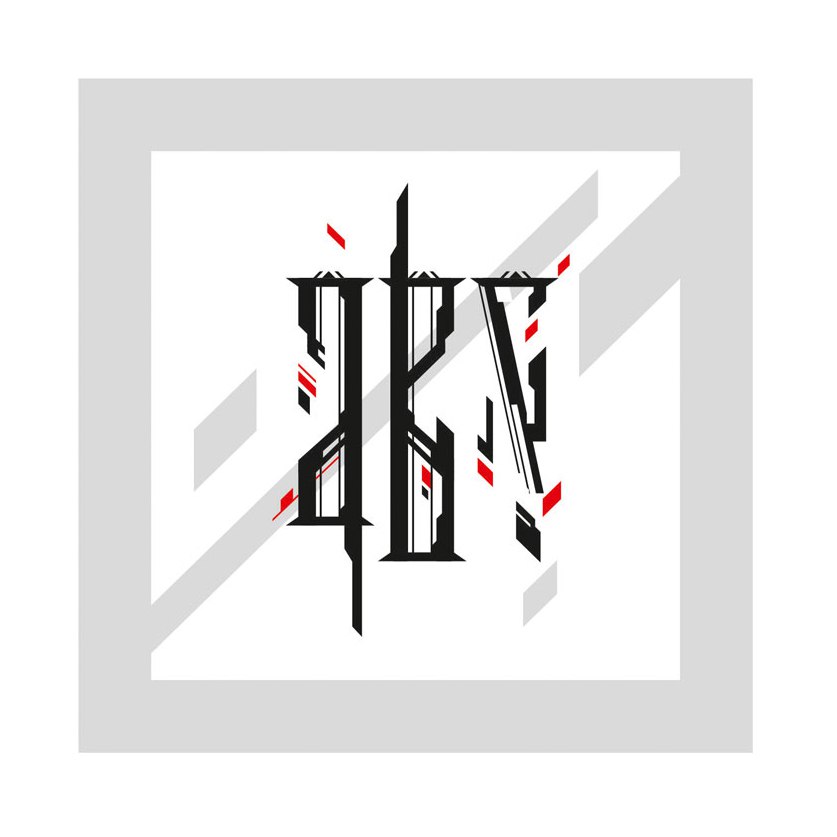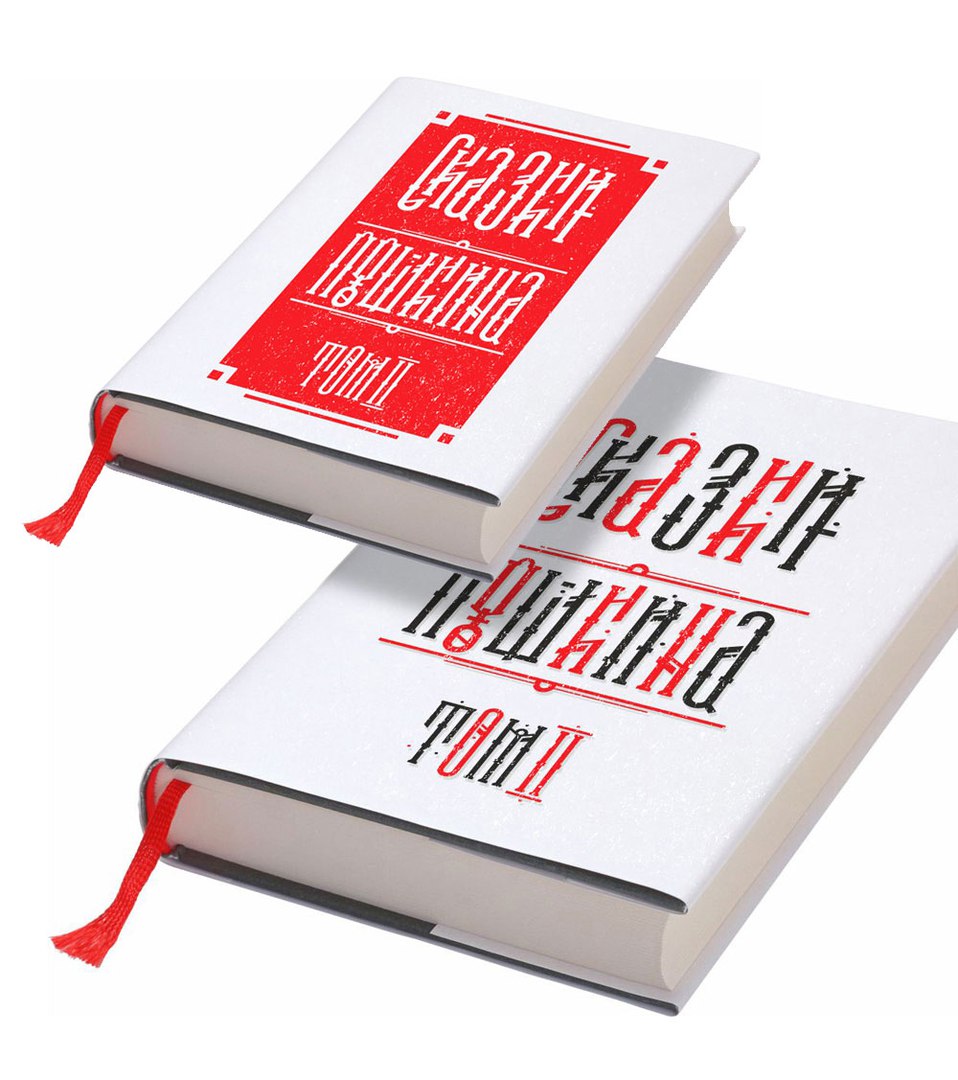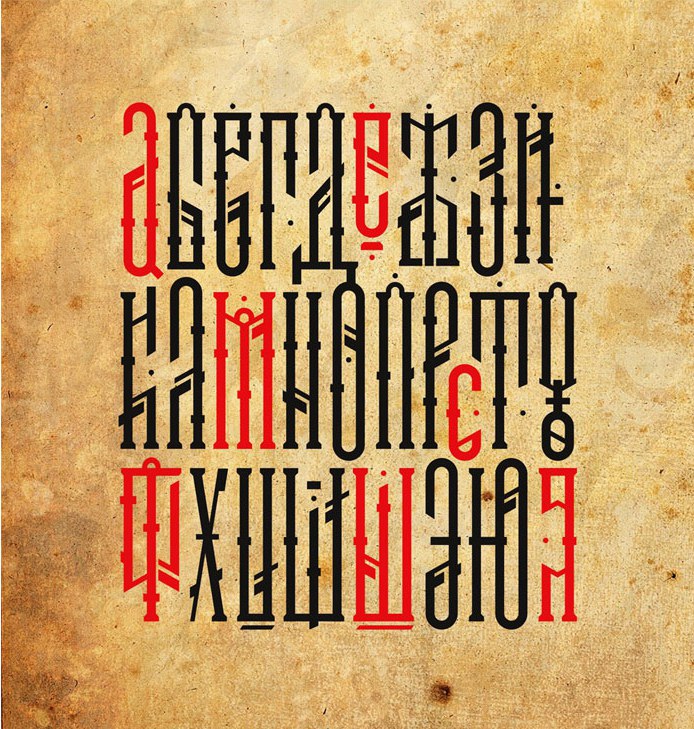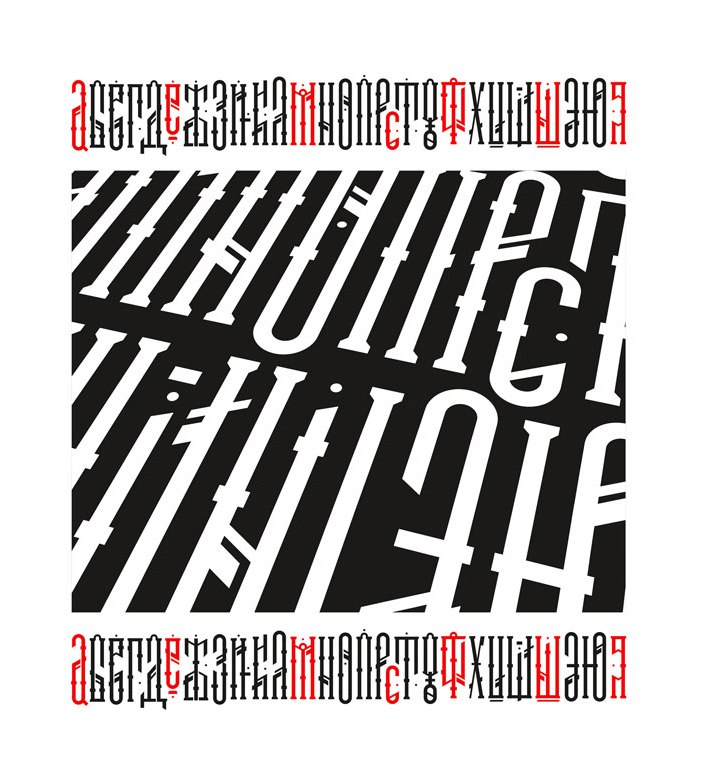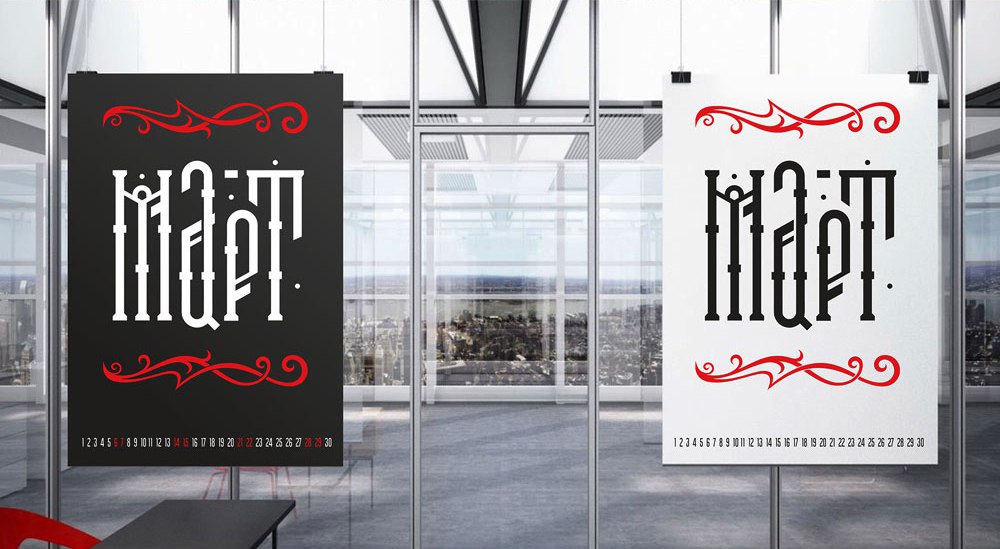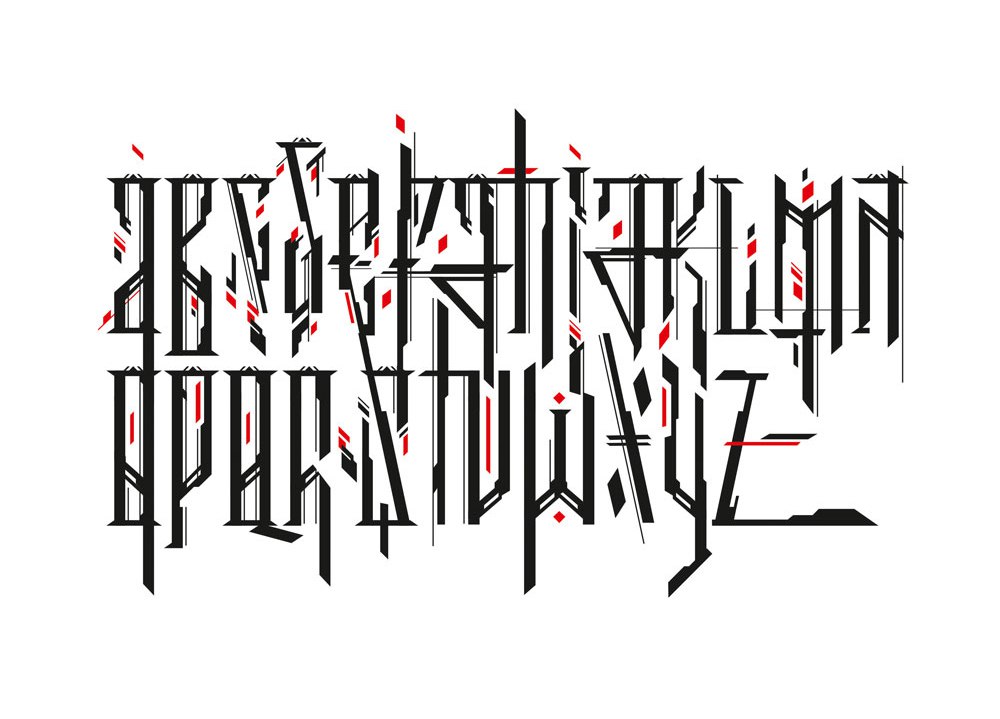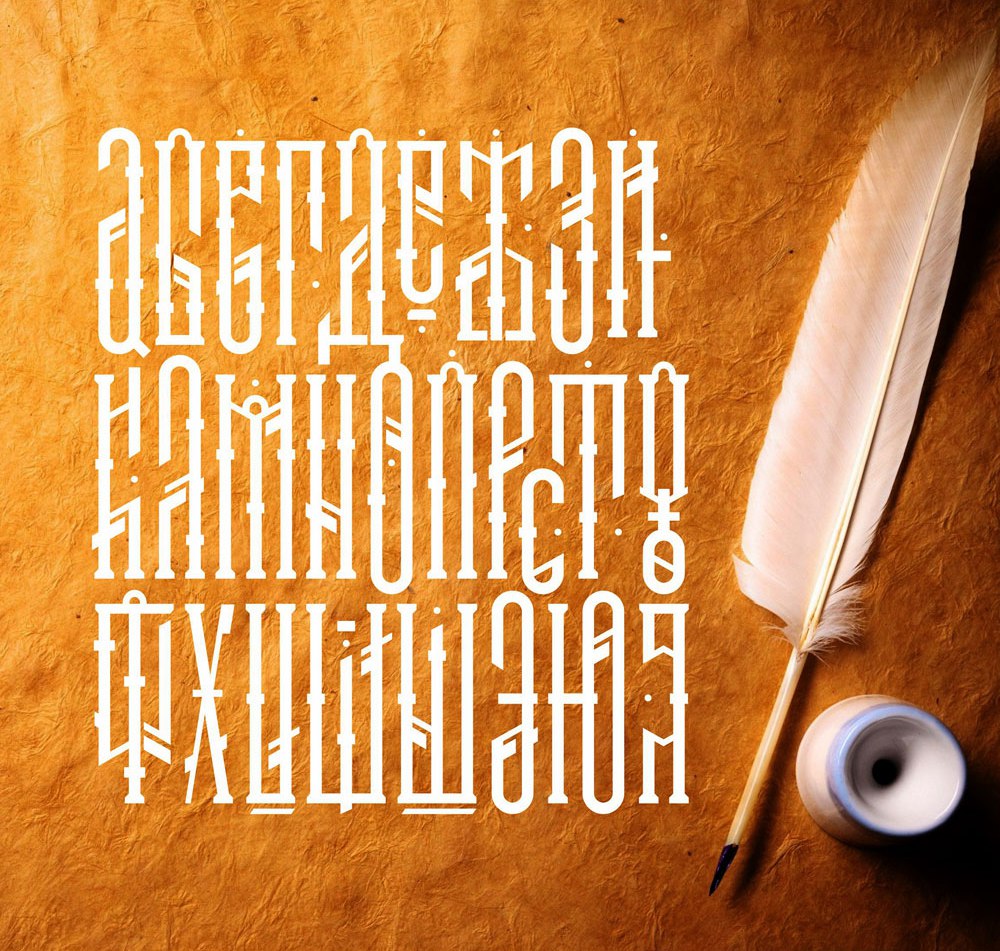
Шрифт Mart (Латиница, Кириллица)
Авторская версия русского орнаментального шрифта.
Павел Дракунов behance.net/Drakunoff о шрифте: “Мои эксперименты с вязью и русскими шрифтами привели меня к созданию шрифта MART. Создавая его я вдохновлялся работами Андрея Мартынова, классикой русских орнаментов и современными формами. Векторная основа доступна всем для дальнейшего улучшения и самостоятельного развития шрифта.”